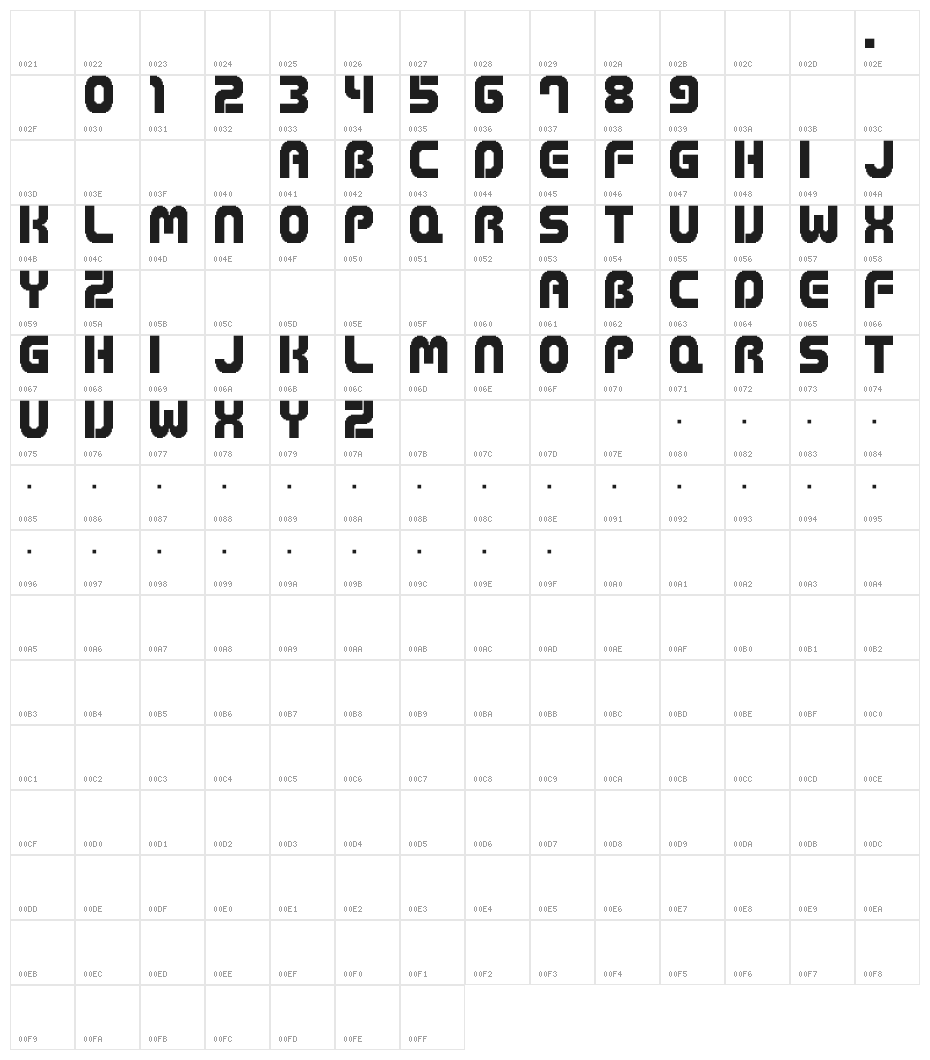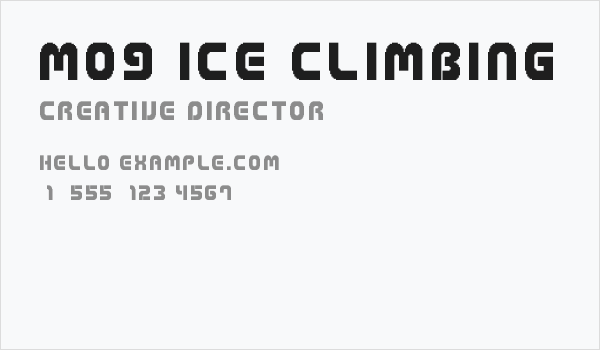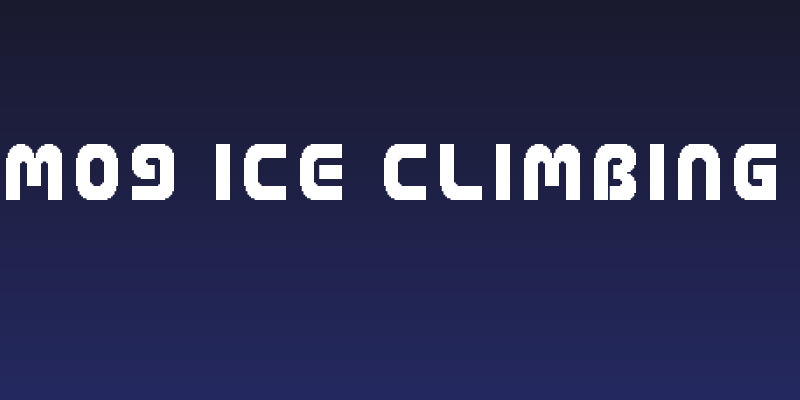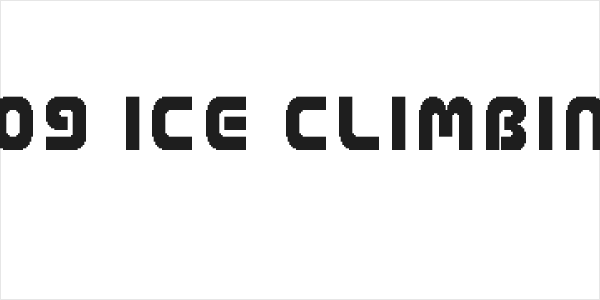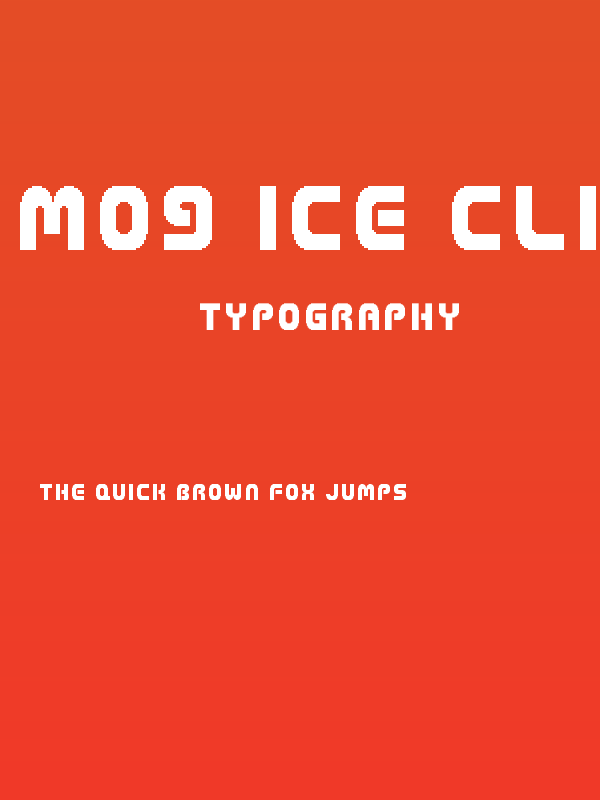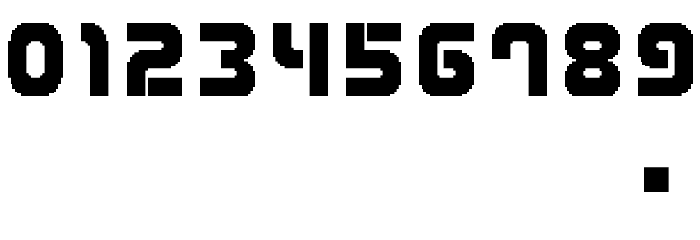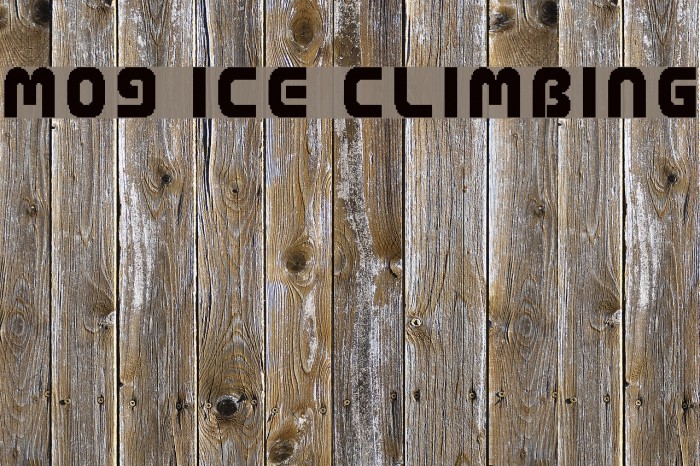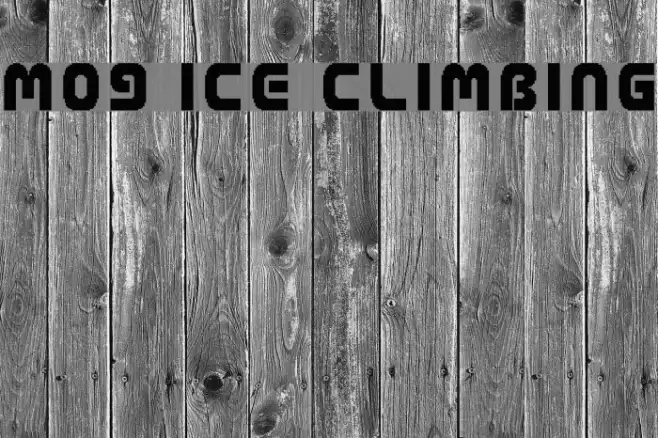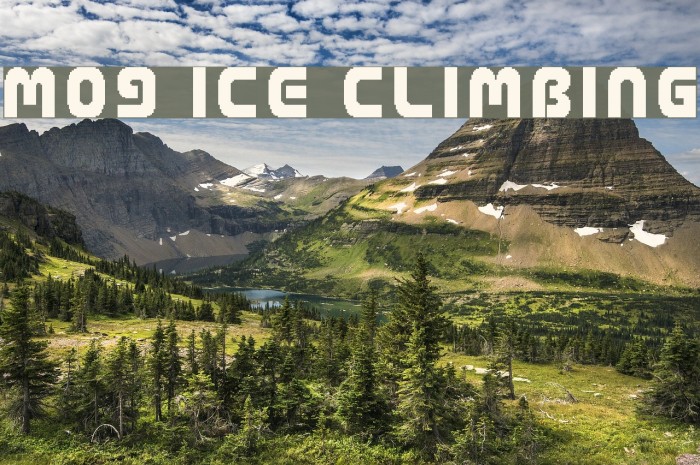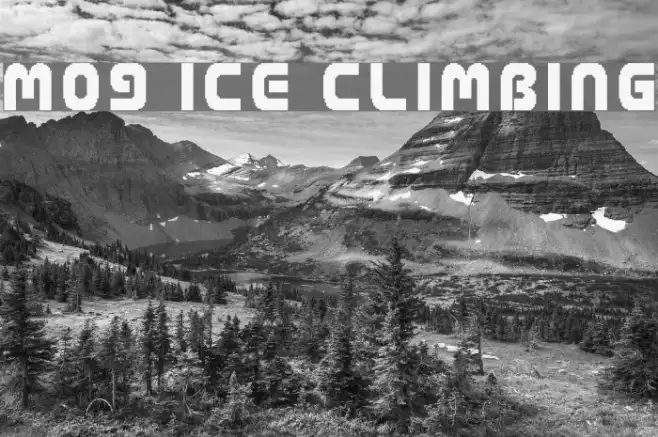
M09_ICE CLIMBING Font
| Proyectos propuestos | Ideal for branding, posters, headlines, and digital interfaces that require a strong, modern presence. |
M09_ICE CLIMBING